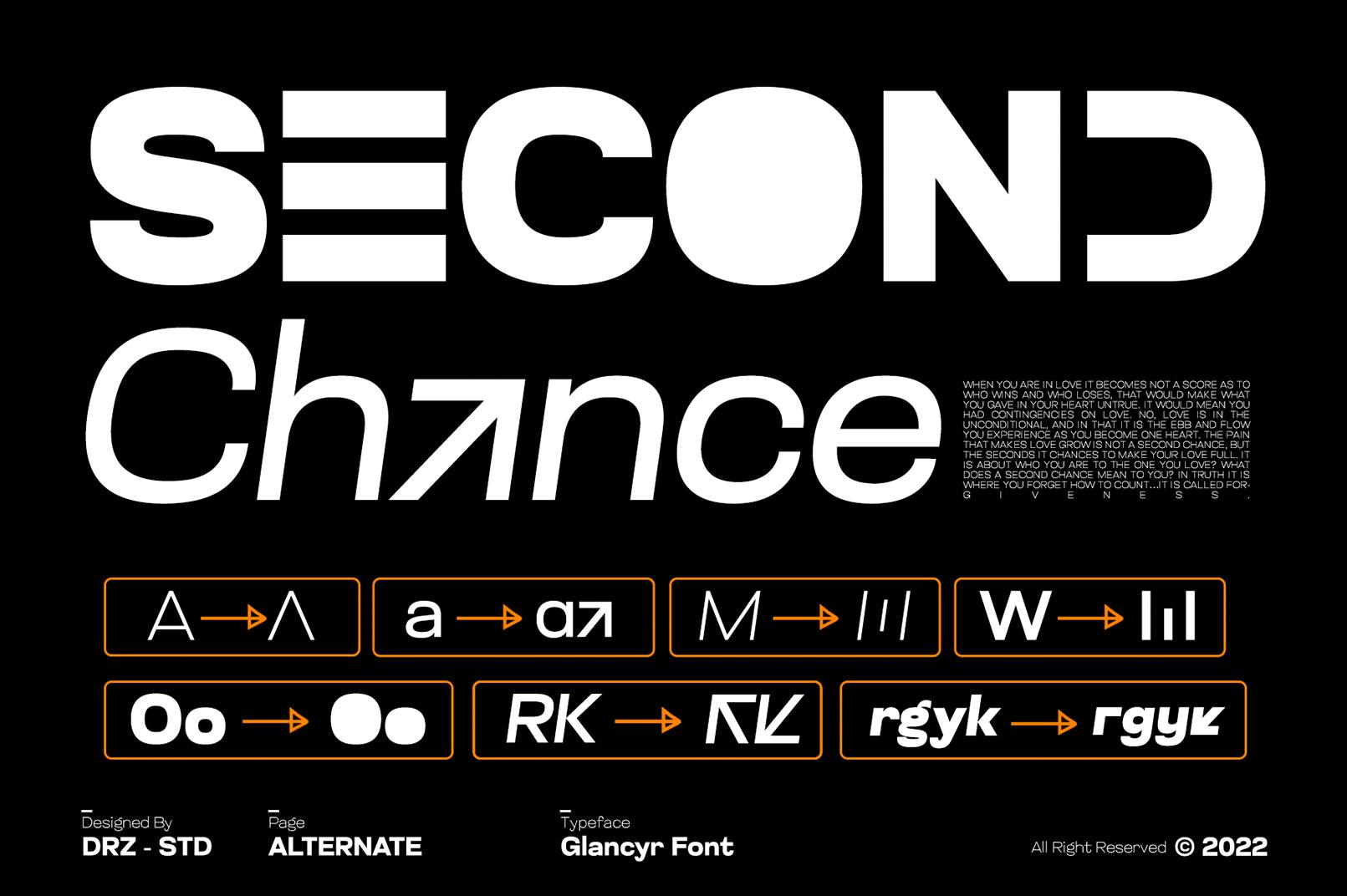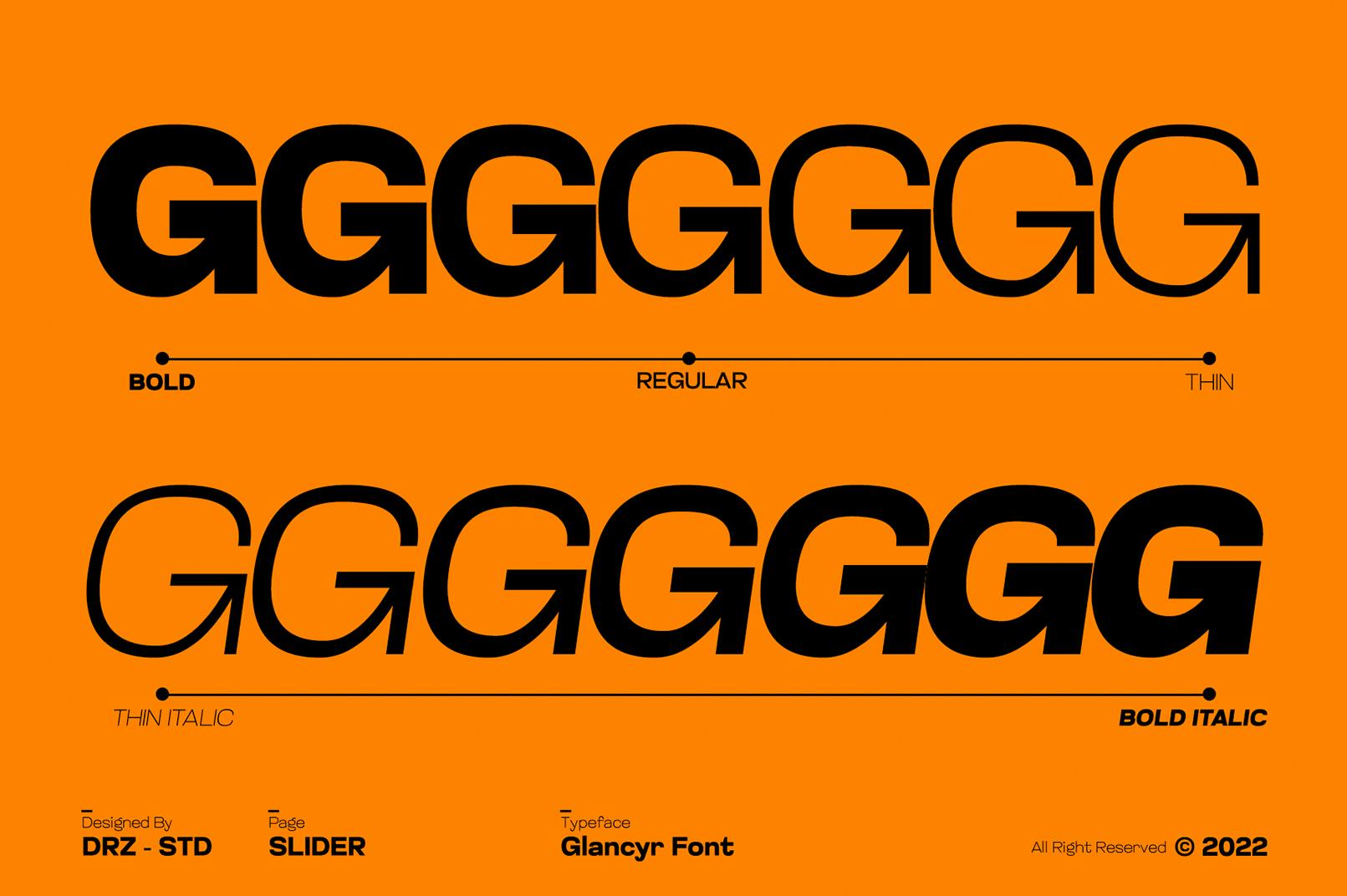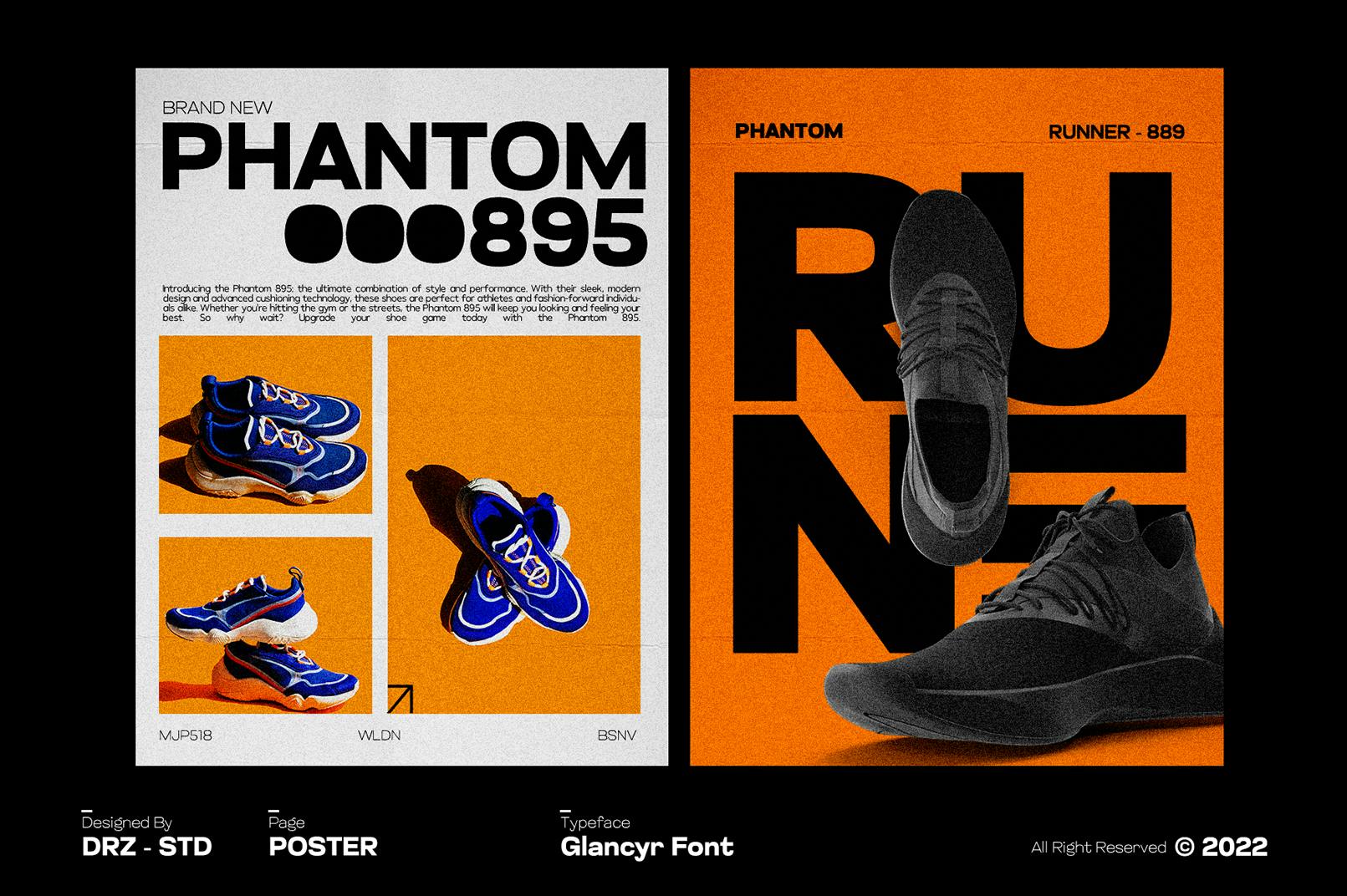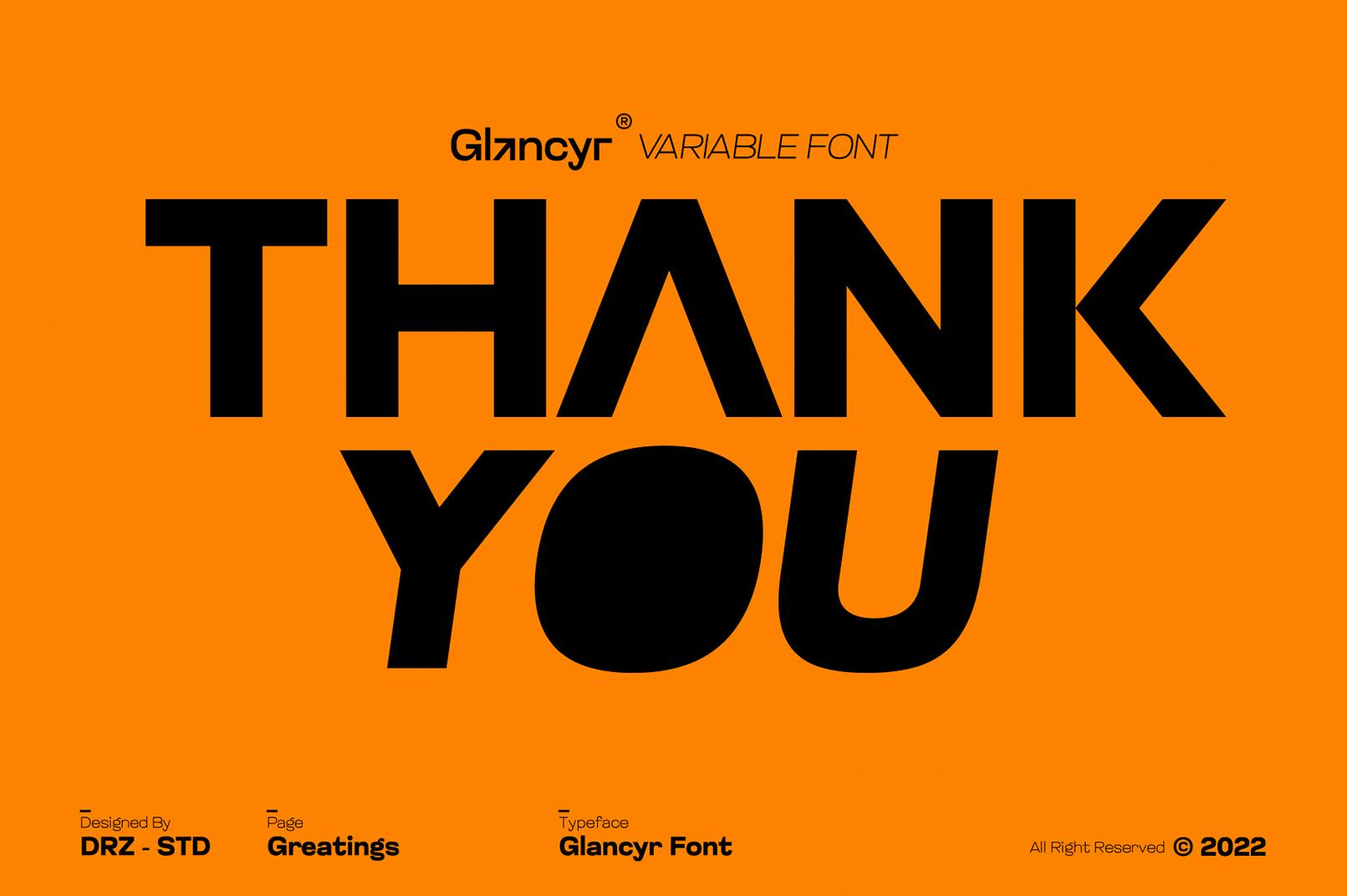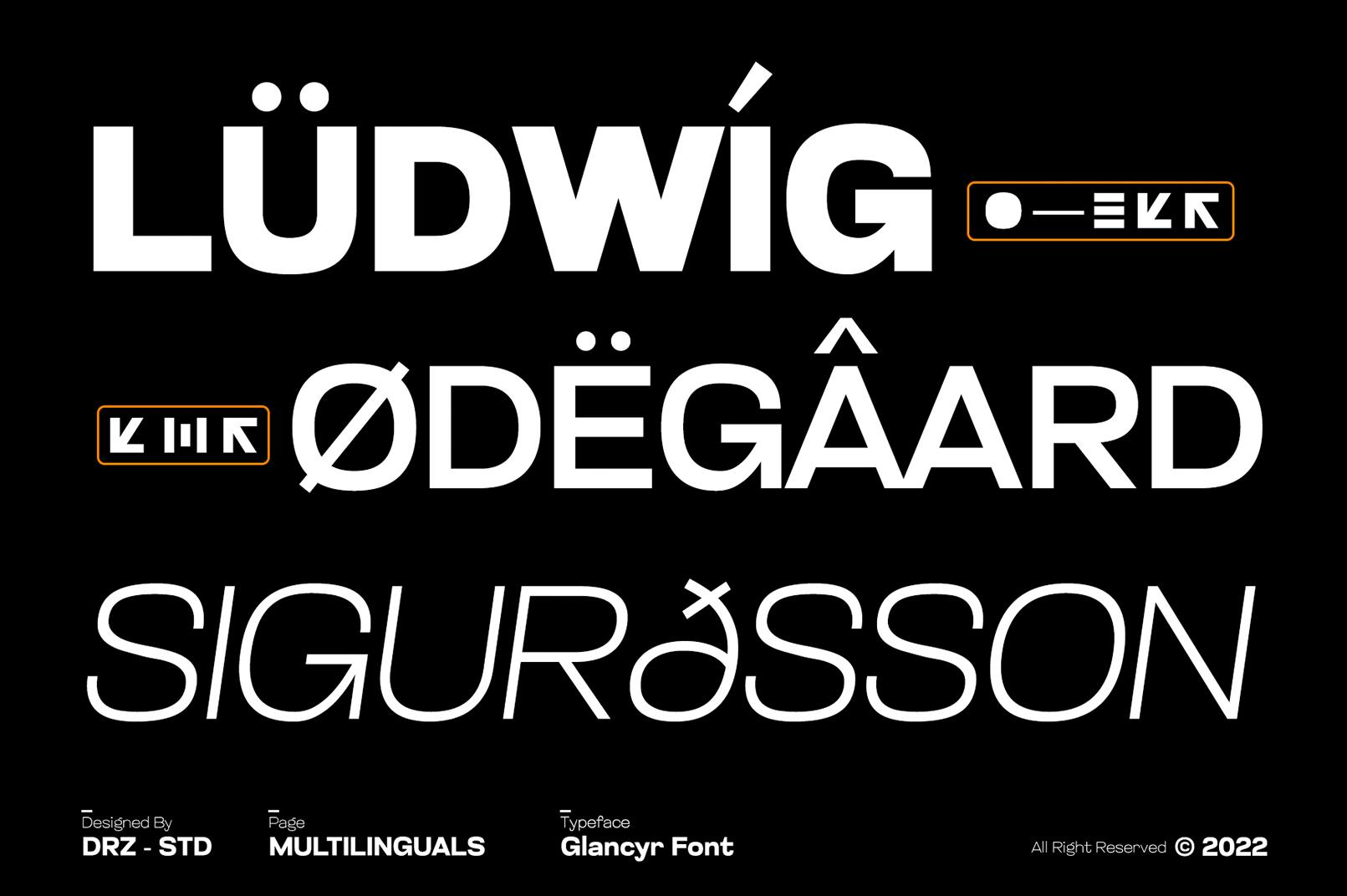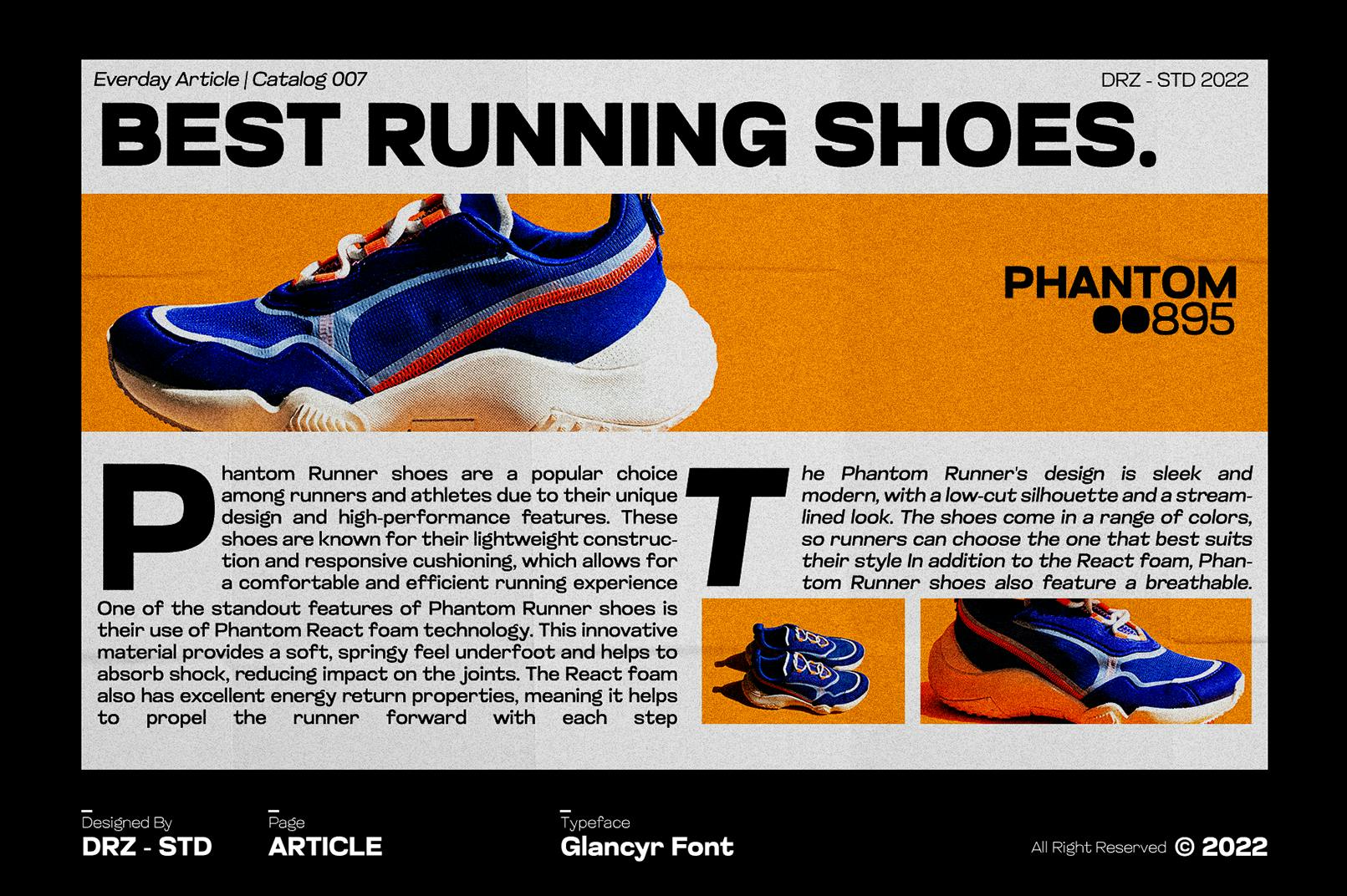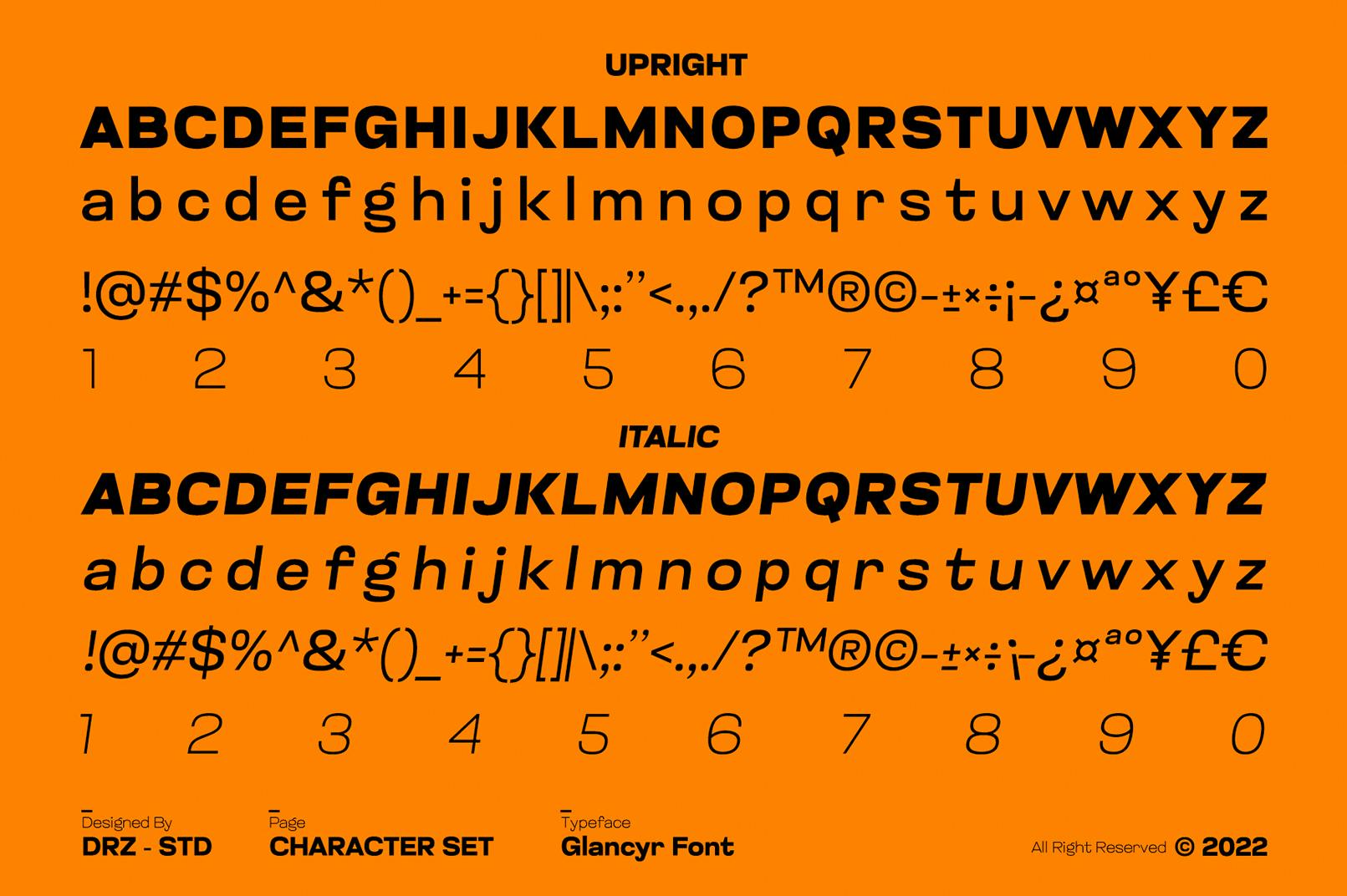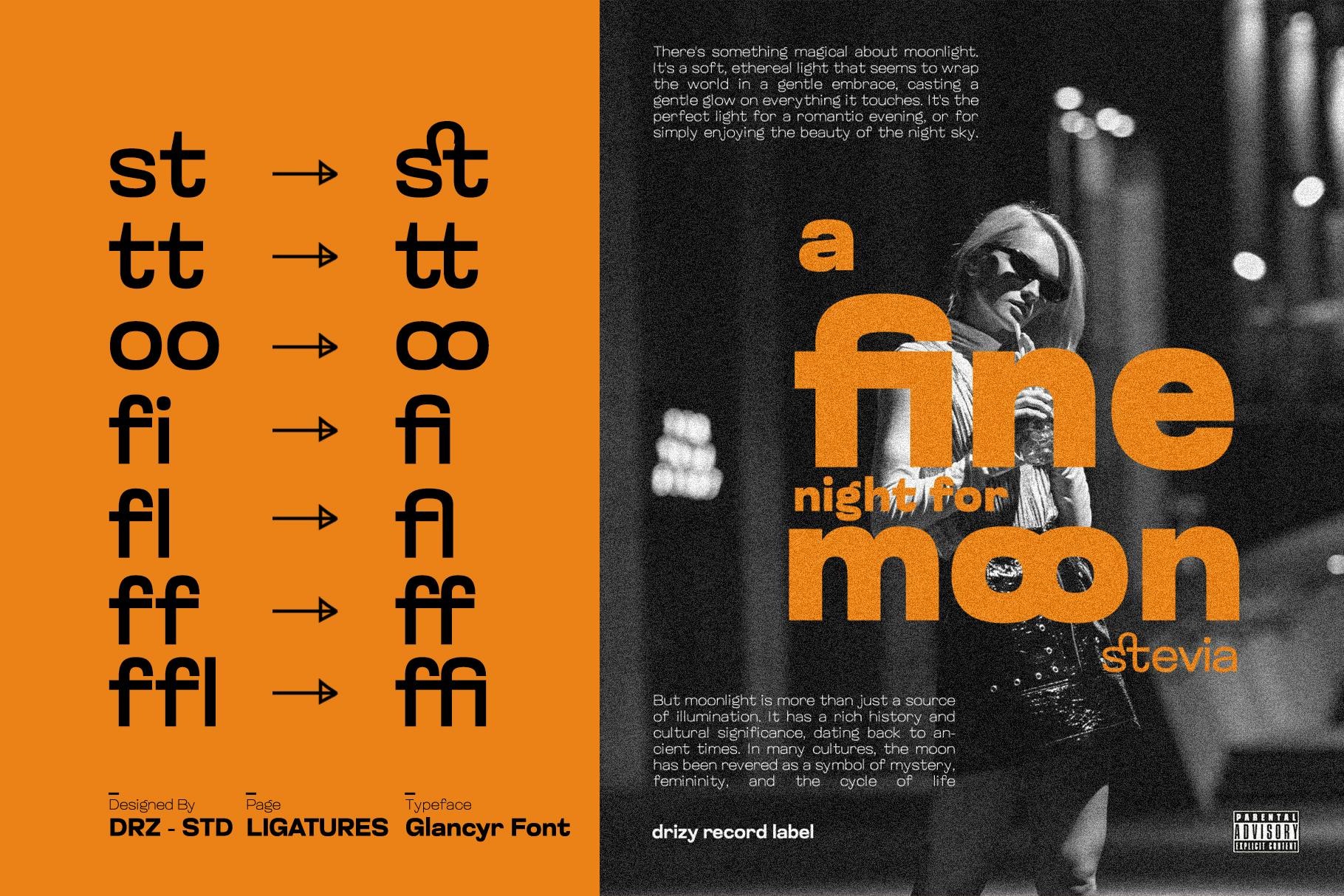
Glancyr Modern Geometric Font
فونت Glancyr، انتخابی مناسب برای پروژه‌های طراحی شما.
فونت Glancyr - هندسی مدرن
فونت Glancyr از استودیوی Drizy ارائه‌دهنده تمامی سبک‌هایی است که برای پروژه‌های خود نیاز دارید.
ویژگی‌های فونت Glancyr:
• راست و کج
• نشانک‌ها و اعداد
• پشتیبانی چندزبانه
• لیگاتورها
• نسخه‌های جایگزین